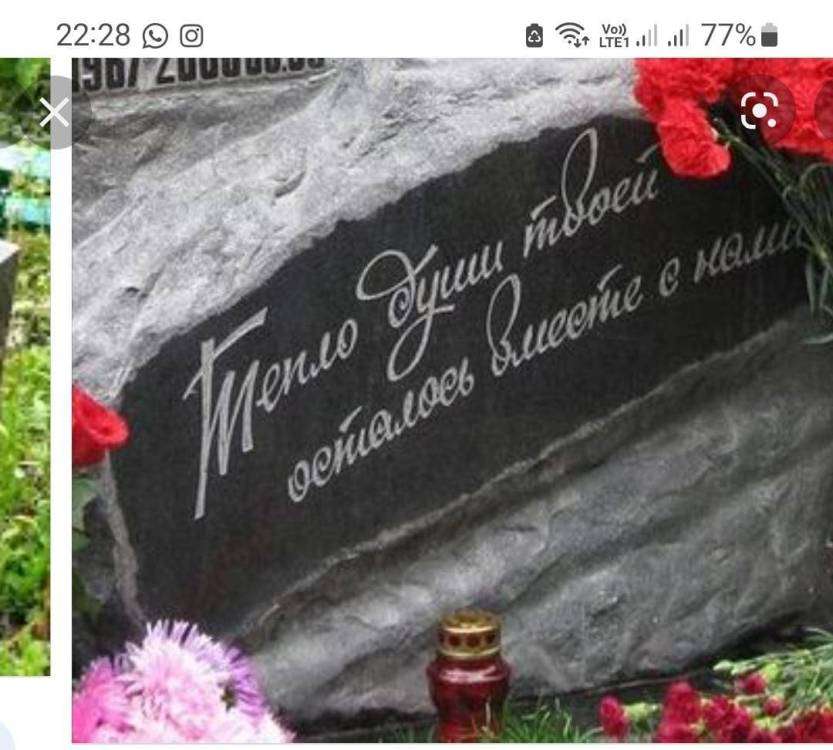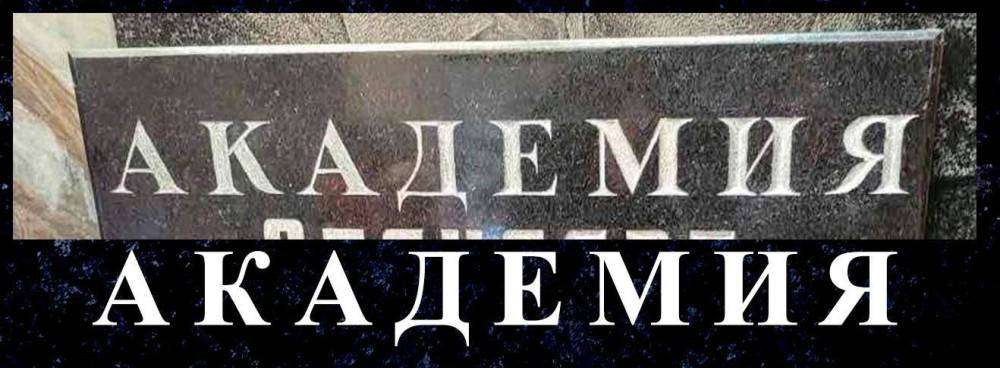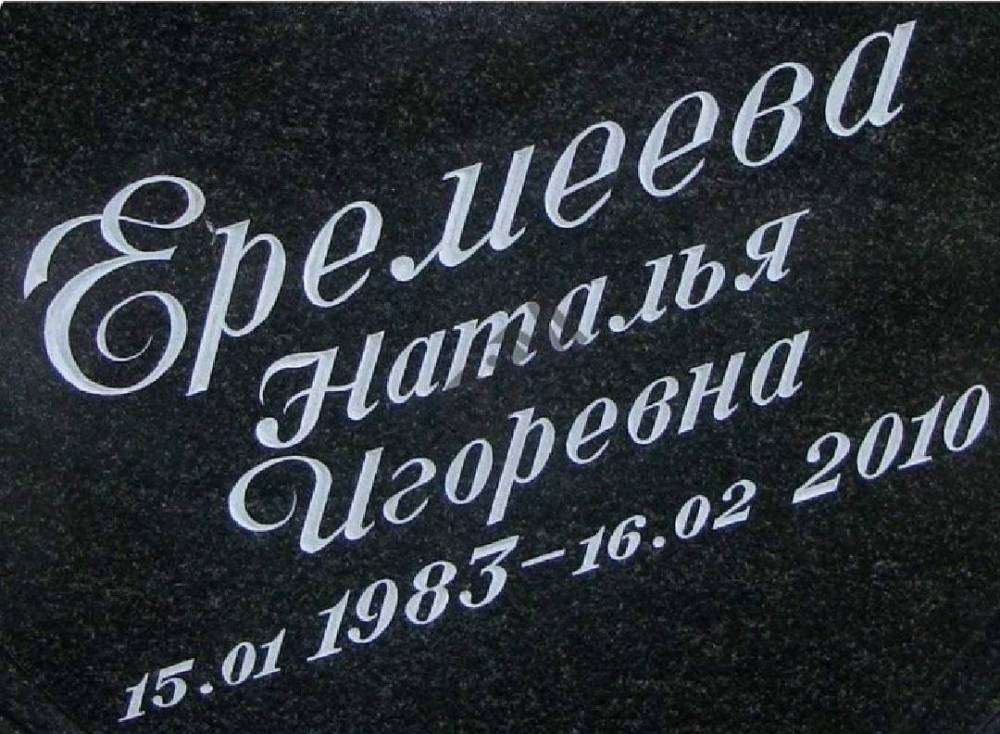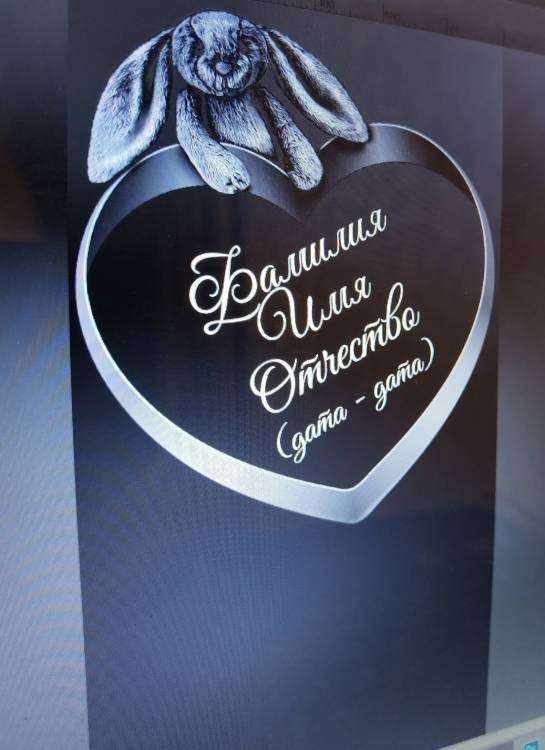
Помогите найти шрифт!
7 часов назад, Агита сказал:
Я у себя перерыла все шрифты, есть похожие , но такого нет
Rodchenko
@WERTY у меня такого шрифта нет...
@Агита скачай)
По нашему региону не востребован, нуу не откажусь ... а в друг понадобится)
Всем день добрый подскажите пожалуйста что за шрифт8f6fac2b-1c69-4e40-aa0a-b7303b60b3b2.thumb.jpg.38a309334a62d8c381f9d5cd090ce338.jpg
Как скучно я живу... Я тож такой хочу:hmm:
1 час назад, Агита сказал:
Как скучно я живу... Я тож такой хочу:hmm:
Куда?:aai:
@WORLD IN STONE  шрифт такой хочу который ищет Loado )))):girl_dance:
26.04.2022 в 14:10, Sofiya сказал:
Шрифт семейства Molot. Отталкивайтесь от этого. На старых памятниках он больше всего похож, даже если он вручную набит.
@Loado  тут ещё и ручная работка) ... молоточек и скарпель...
Да уже с кем не общался говорят ручная работа.
всем привет подскажите что за шрифт?
@Aidar606  Искаженный вручную Times New Roman
43 минуты назад, WERTY сказал:
@Aidar606  Искаженный вручную Times New Roman
вроде станочный должен быть
16 минут назад, Aidar606 сказал:
вроде станочный должен быть
станок научился бить как скарпелью?)
У меня такое было, гравировку надписей  станком в два прохода зделали, пришли, посмотрели... а можно углубленно?!:blink:
Я конечно сразу растерялась, а тут мысля ,ручная же да ещё скальпельками!!  ответ мой в два дорого))
...согласны!
Ну и все! Клиент доволен, зделали по глубже не меняя шрифт))
@Агита может быть и такое, но тут явно шрифт Таймс с искаженными К и Я и засечки чуть грубее... и четко просматривается углубления скарпелями по центру букв
К и Я могли с другого шрифта взять, так тоже извращаются, не раз уже с таким сталкивался)
Тут, например, шрифт Baskerville, а буквы Л и Д с другого шрифта...
@WERTY бывает, меня тож просят заглавную иногда подобрать к основному шрифту по красивше))
2 часа назад, WERTY сказал:
@Агита может быть и такое, но тут явно шрифт Таймс с искаженными К и Я и засечки чуть грубее... и четко просматривается углубления скарпелями по центру букв
К и Я могли с другого шрифта взять, так тоже извращаются, не раз уже с таким сталкивался)
Тут, например, шрифт Baskerville, а буквы Л и Д с другого шрифта...
тогда из какого шрифта буквы К и Я интересно?
хепл плиз
Ребят есть у кого достойный шрифт на детский памятник? Чтоб красиво и родителям спокойно?
Ну ладно сама справлюсь...
Думала по быстрому, всего лишь надпись 5 минут, .....  часика два - три,  не  получилось.... манюня... не могу
Вот такой красиво сочетается с детским оформлением. Шрифт good vibes pro
зайчик конечно, еще и цвет подходящий, дизайнеру видимо фильмы про зомби нравятся